Anda bisa menggunakannya untuk mempelajari atau mengajarkan isyarat alfabet untuk berbagai negara atau dalam berbagai bahasa. Karena seperti bahasa lisan, bahasa isyarat juga bisa berbeda-beda di setiap negara.
Bk Bisindo Font
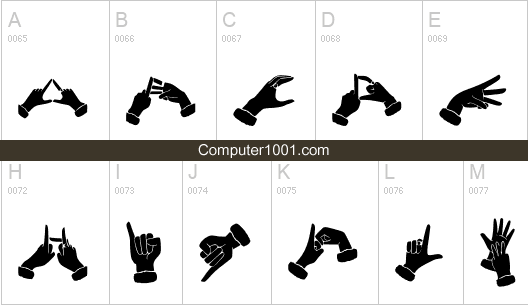
Font Bahasa Isyarat Indonesia (BISINDO) untuk isyarat huruf abjad A – Z.
Bahasa isyarat yang ada di Indonesia memiliki 2 jenis yaitu Bahasa Isyarat Indonesia (BISINDO) dan Sistem Isyarat Bahasa Indonesia (SIBI).
BISINDO merupakan bahasa ibu yang tumbuh secara alami pada kalangan komunitas Tuli di Indonesia.
Sedangkan SIBI merupakan bahasa isyarat yang diadopsi dari American Sign Langauge (ASL) dengan penambahan awalan dan akhiran dan beberapa modifikasi lainnya.
Fingerspelling Font
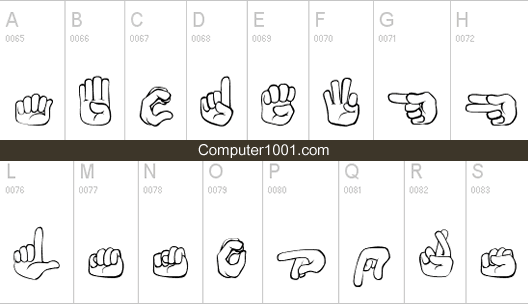
Font Fingerspelling dibuat berdasarkan Bahasa Isyarat Amerika (American Sign Language / ASL).
Memiliki alfabet lengkap, angka 0 – 9, dan beberapa tanda lainnya, seperti isyarat tangan simbol hati atau cinta.
Auslan Finger Spelling Font
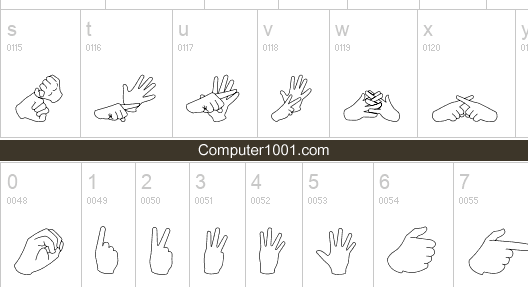
Font simbol untuk isyarat tangan Auslan (Australian Sign Language / Bahasa Isyarat Australia).
Selain memiliki isyarat huruf abc, font ini juga memiliki isyarat untuk angka 0 – 9.
Sign Language Fonts
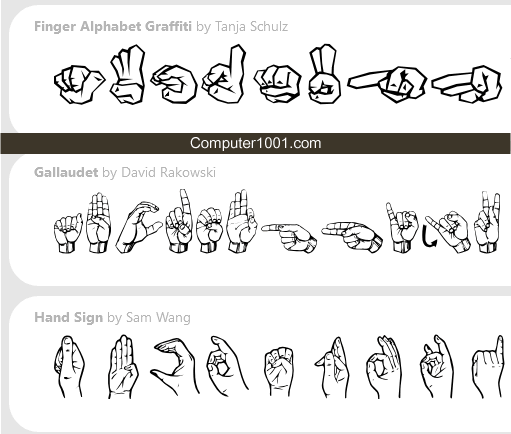
Sutton Fingerspelling Fonts
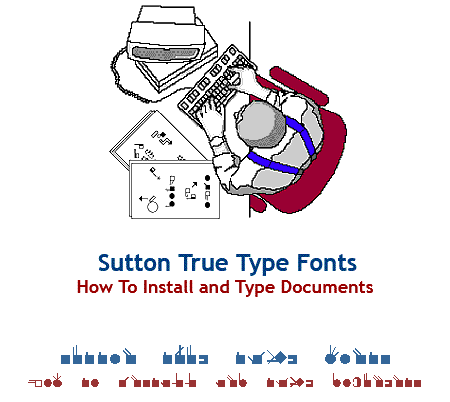
Font isyarat tangan Sutton tersedia untuk pengguna Windows dan Macintosh dalam 18 bahasa berikut:
- American Sign Language (Bahasa isyarat Amerika)
- British Sign Language (Bahasa Isyarat Inggris)
- Belgian Flemish Sign Language (Bahasa Isyarat Flemish Belgia)
- Belgian French Sign Language (Bahasa Isyarat Prancis Belgia)
- Brazilian Sign Language (Bahasa Isyarat Brasil)
- Danish Sign Language (Bahasa Isyarat Denmark)
- French Sign Language (Bahasa Isyarat Prancis)
- German Sign Language (Bahasa Isyarat Jerman)
- Irish Sign Language (Bahasa Isyarat Irlandia)
- Italian Sign Language (Bahasa Isyarat Italia)
- Japanese Sign Language (Bahasa Isyarat Jepang)
- Mexican Sign Language (Bahasa Isyarat Meksiko)
- Nicaraguan Sign Language (Bahasa Isyarat Nikaragua)
- Norwegian Sign Language (Bahasa Isyarat Norwegia)
- Portuguese Sign Language (Bahasa Isyarat Portugis)
- Spanish Sign Language (Bahasa Isyarat Spanyol)
- Swedish Sign Language (Bahasa Isyarat Swedia)
- Swiss-German Sign Language (Bahasa Isyarat Swiss-Jerman)